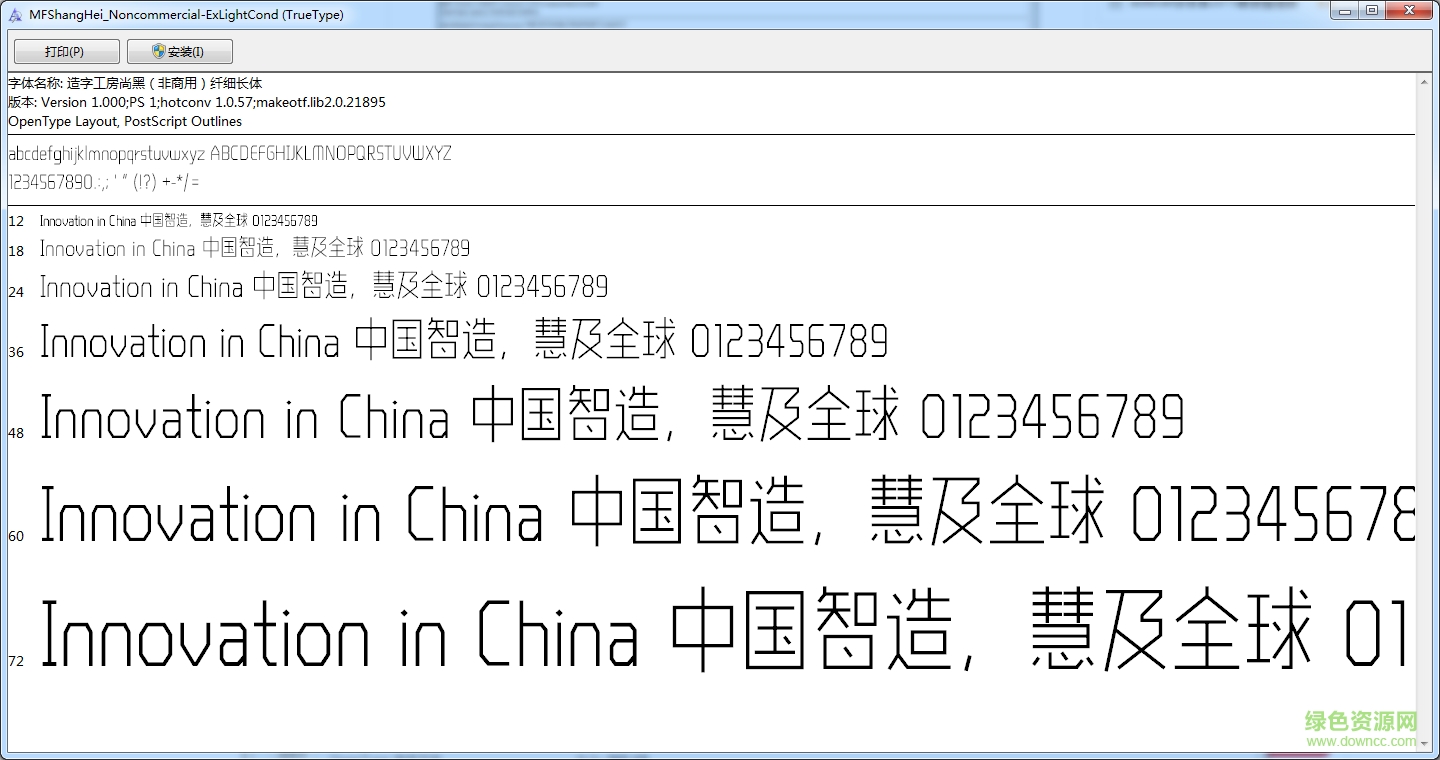
造字工房尚黑纖細(xì)長(zhǎng)體
造字工房尚黑纖細(xì)長(zhǎng)體是一款端正美觀的簡(jiǎn)體字體,此款字體字型清秀、結(jié)構(gòu)簡(jiǎn)單,擁有完整的字庫(kù),支持中文、英文、數(shù)字輸入功能,安裝非常簡(jiǎn)單,喜歡的朋友歡迎來(lái)綠色資源網(wǎng)下載!